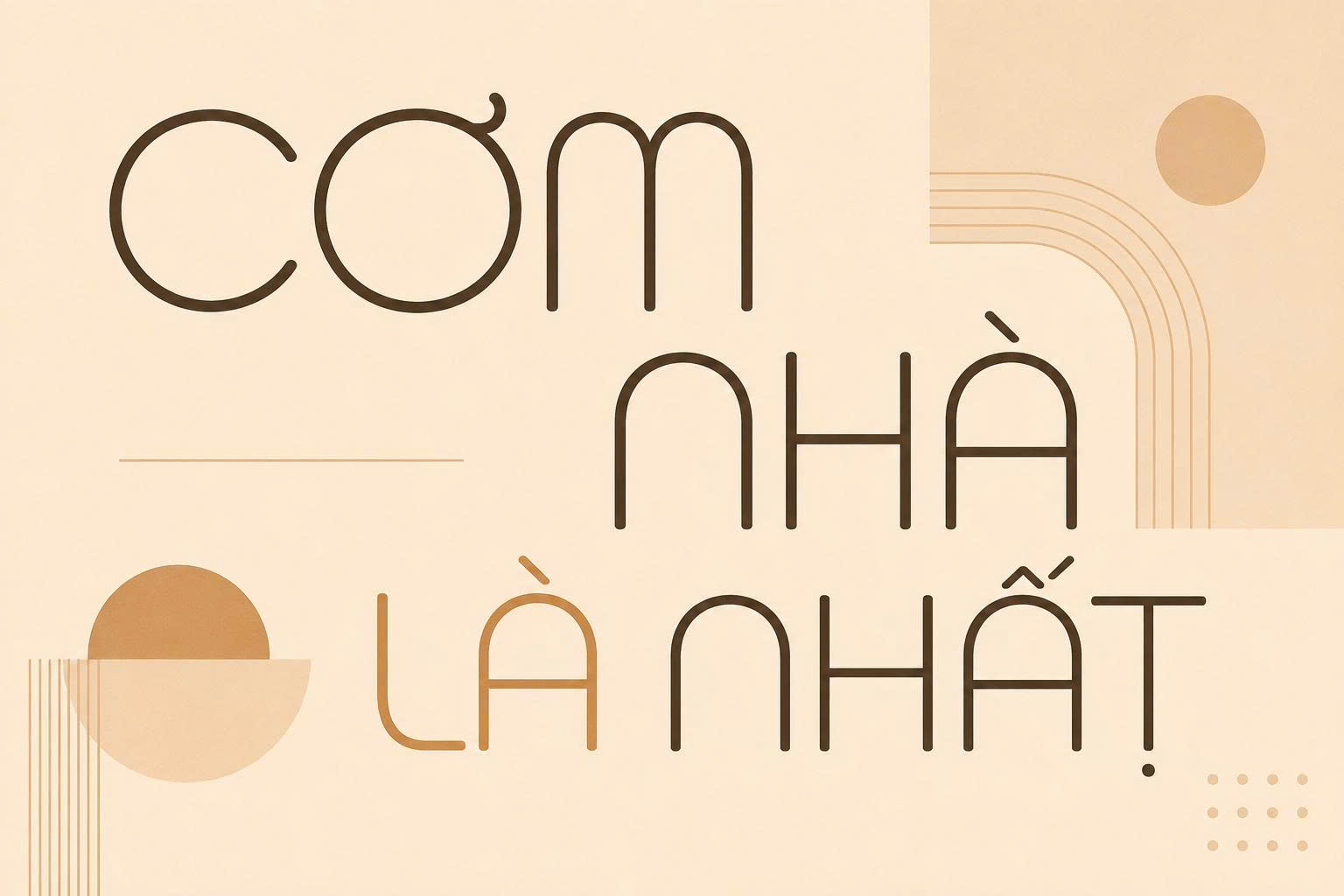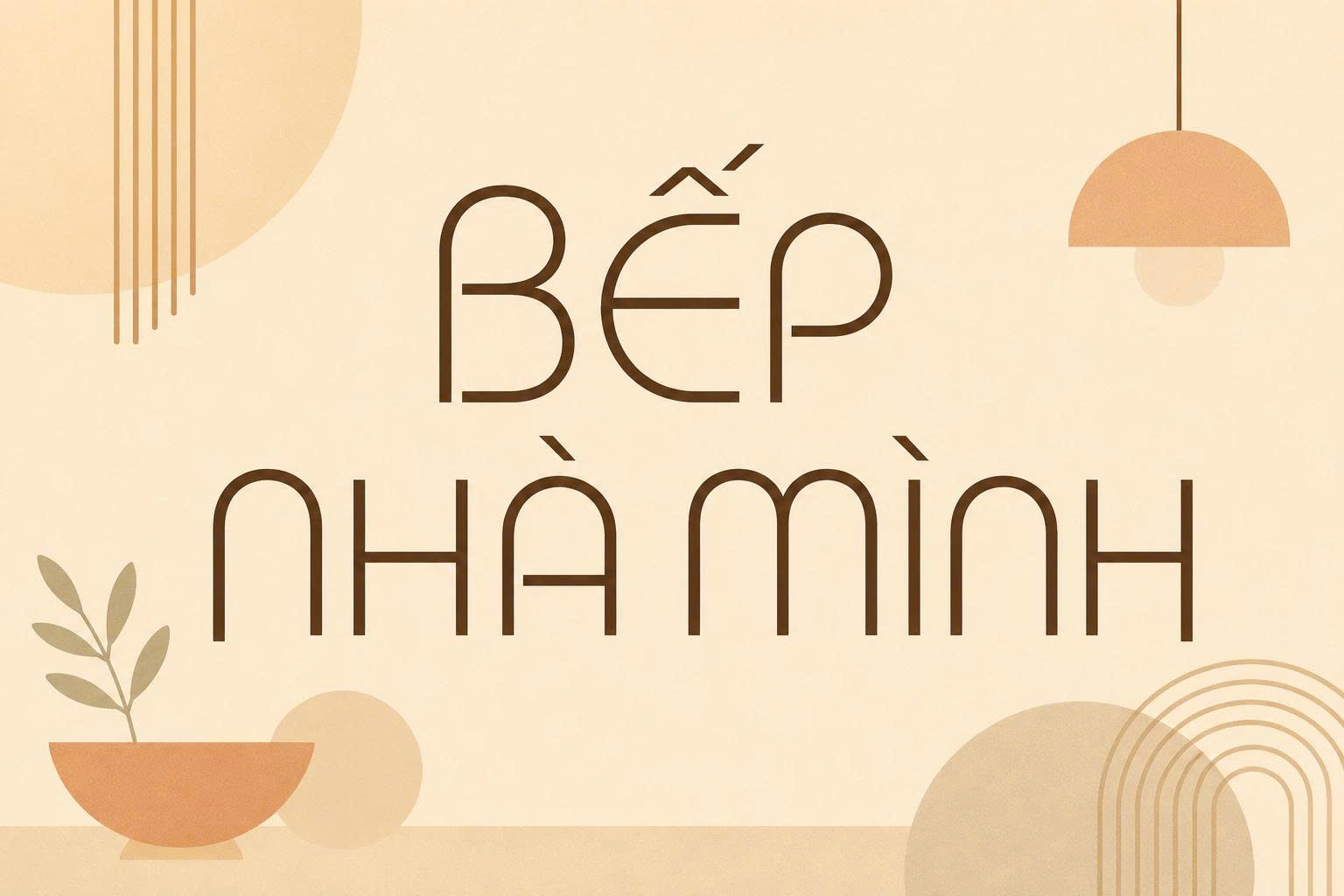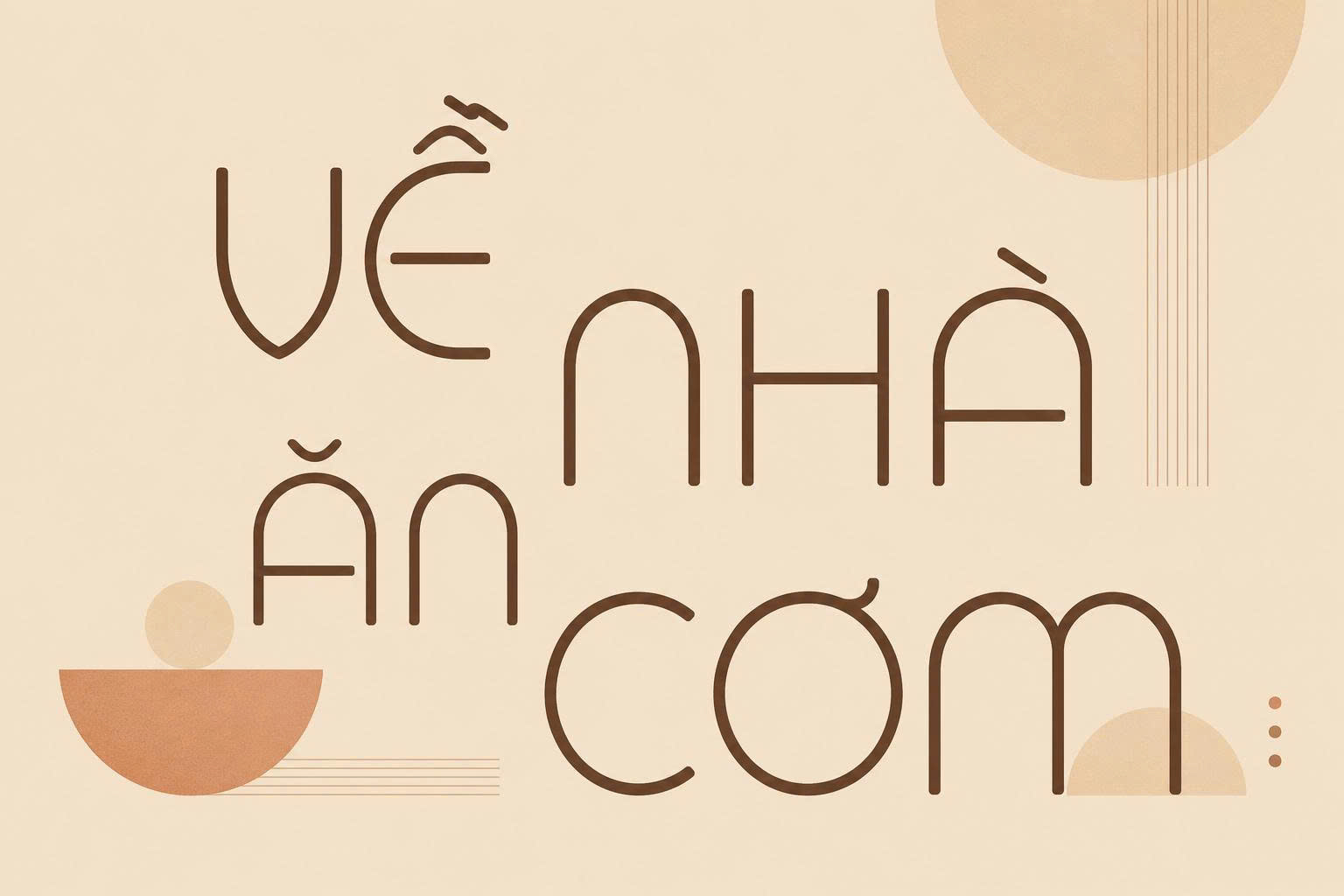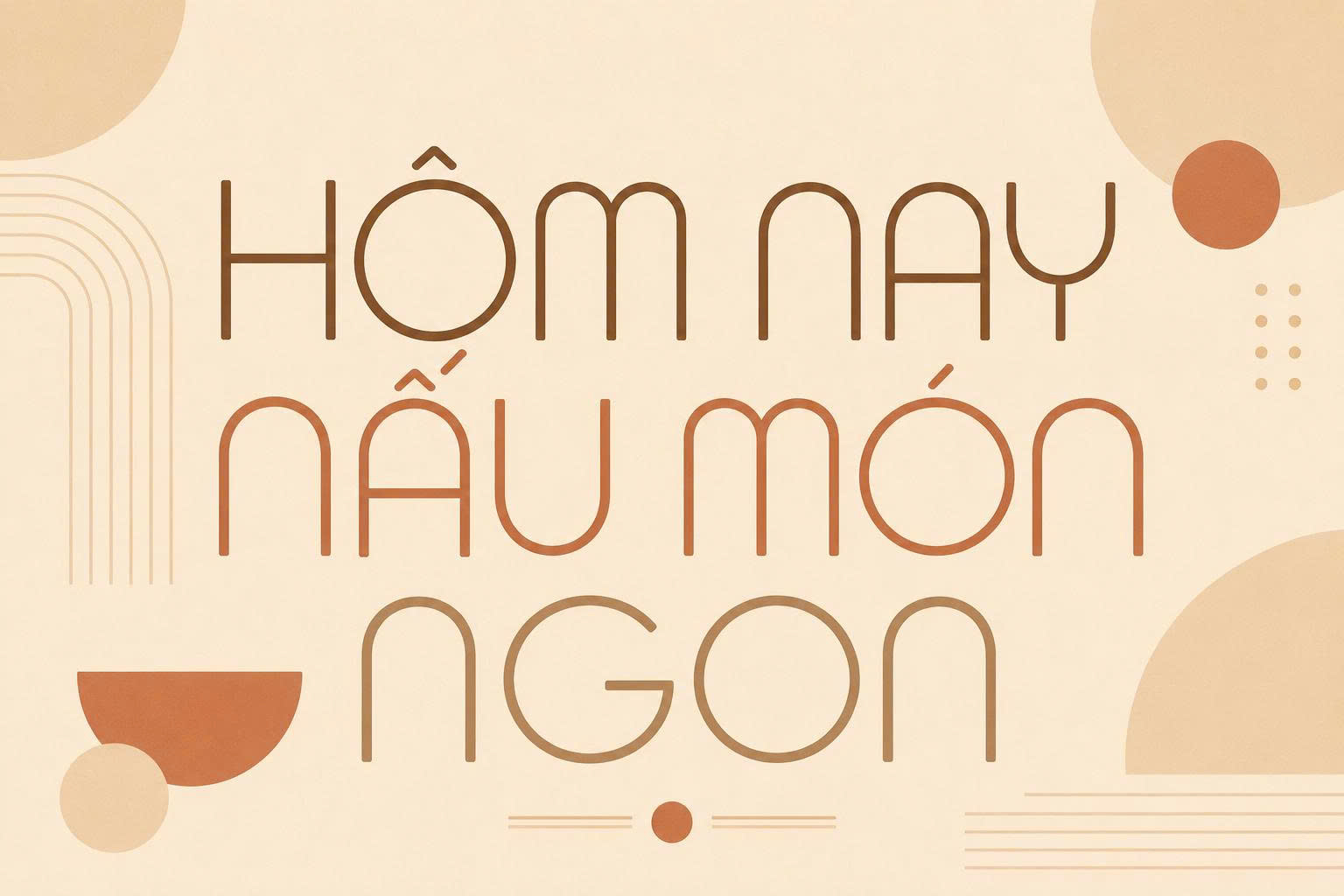
Font Bauhaus Việt hóa là bộ phông chữ không chân (Sans-serif) kinh điển lấy cảm hứng từ trường phái nghệ thuật Bauhaus nổi tiếng của Đức vào đầu thế kỷ 20. Với đặc trưng là cấu trúc hình học tối giản, các đường nét bo tròn hoàn hảo và tinh thần “công năng đi trước thẩm mỹ”, Bauhaus là lựa chọn hàng đầu cho các thiết kế logo, poster kiến trúc và bao bì sản phẩm hiện đại. Doozypack.vn cung cấp link tải bộ font Bauhaus hỗ trợ tiếng Việt chuẩn, giúp bạn sở hữu phông chữ đẳng cấp mà không gặp bất kỳ lỗi hiển thị dấu thanh nào trên bản vẽ thiết kế.
Lịch sử và đặc điểm thẩm mỹ của font Bauhaus Việt hóa
Để ứng dụng hiệu quả bộ font này, trước hết bạn cần hiểu rõ linh hồn của nó nằm ở sự kết hợp giữa kỹ thuật công nghiệp và nghệ thuật đồ họa đương đại.
Tư duy thiết kế hình học tối giản
Đặc trưng lớn nhất của font Bauhaus Việt hóa là cấu trúc chữ dựa trên những hình khối cơ bản: hình tròn, hình vuông và đường thẳng. Các ký tự như ‘o’, ‘c’, ‘p’ thường được tạo hình từ những vòng tròn gần như tuyệt đối, mang lại cảm giác vô cùng cân đối và hiện đại. Phong cách này không chỉ giúp bản thiết kế trông sạch sẽ mà còn truyền tải thông điệp về sự minh bạch và sáng tạo đột phá.
Khả năng hiển thị mạnh mẽ và phá cách
Bauhaus sở hữu độ dày nét đồng đều, giúp phông chữ này có sự vững chãi và “sức nặng” về thị giác rất tốt. Khác với các dòng font không chân truyền thống, Bauhaus loại bỏ hoàn toàn các chi tiết rườm rà, tập trung vào việc tạo ra nhịp điệu Typography mạnh mẽ. Chính sự phá cách này giúp các tiêu đề bao bì trở nên cực kỳ nổi bật trên kệ hàng.
Tại sao designer nên sử dụng font Bauhaus hỗ trợ tiếng Việt?
Việc lựa chọn một bộ font Bauhaus tiếng Việt chỉn chu mang lại nhiều lợi ích thực tế cho quy trình thiết kế và sản xuất bao bì tại Doozypack.vn:
- Giải quyết triệt để lỗi font: Bản Việt hóa chuẩn đảm bảo các ký tự đặc thù như “ơ, ư, đ” và các dấu thanh được đặt ở vị trí cân đối, không làm biến dạng hình khối hình học của phông chữ gốc.
- Đồng bộ nhận diện thương hiệu: Giúp doanh nghiệp duy trì ngôn ngữ thiết kế tối giản từ logo, website đến hộp giấy sản phẩm một cách nhất quán.
- Tối ưu hiệu quả in ấn: Cấu trúc nét chữ chắc chắn của Bauhaus hoạt động ổn định trên nhiều công nghệ in như in lụa, in Offset hay in kỹ thuật số.
| Biến thể Font | Đặc điểm thị giác | Mục đích sử dụng đề xuất tại Doozypack.vn |
| Bauhaus Light | Thanh mảnh, hiện đại | Dùng cho nội dung mô tả, địa chỉ sản xuất trên vỏ hộp. |
| Bauhaus Medium/Bold | Vững chãi, rõ nét | Dùng cho tiêu đề chính, tên sản phẩm trên túi giấy. |
| Bauhaus Heavy | Rất đậm, ấn tượng | Dùng làm Logo hoặc các slogan ngắn cần thu hút thị giác mạnh. |
Tư vấn từ xưởng in: Nếu bạn thiết kế bao bì in trên chất liệu giấy nhám như giấy Kraft, hãy ưu tiên dùng biến thể Bauhaus Medium trở lên. Độ dày nét vừa đủ sẽ giúp các góc bo tròn không bị mất chi tiết khi mực in thấm vào thớ giấy thô.
03 Ứng dụng font Bauhaus tiếng Việt trong in ấn bao bì tại Doozypack.vn
Sự tối giản và hiện đại của Bauhaus mang lại hiệu quả thị giác đặc biệt trên các ấn phẩm thực tế do Doozypack.vn sản xuất:
- Hộp quà tặng tối giản (Minimalist Box): Sự kết hợp giữa font Bauhaus và kỹ thuật ép kim bạc trên nền hộp mờ tạo nên vẻ ngoài cực kỳ sang trọng và tinh tế.
- Bao bì sản phẩm công nghệ: Nét chữ hình học của Bauhaus rất tương đồng với các thiết kế linh kiện điện tử hiện đại, tạo nên sự đồng bộ chuyên nghiệp.
- Tem nhãn sản phẩm sáng tạo: Cấu trúc rõ ràng của Bauhaus giúp các bảng thông số trên tem decal trở nên dễ tra cứu và thẩm mỹ hơn cho người tiêu dùng.
03 Lưu ý kỹ thuật khi in ấn font Bauhaus nét dày tại Doozypack.vn
Sản xuất bao bì sử dụng phông chữ hình học như Bauhaus đòi hỏi designer cần lưu ý một số vấn đề kỹ thuật tại xưởng in chuyên nghiệp:
- Kiểm soát độ tràn mực (Dot Gain): Các góc bo tròn và khe hở hẹp của font Bauhaus (đặc biệt là biến thể Heavy) có thể bị mực bít kín nếu in trên giấy Kraft hoặc sóng Carton. Designer nên tăng nhẹ khoảng cách chữ (Tracking) để bản in thông thoáng.